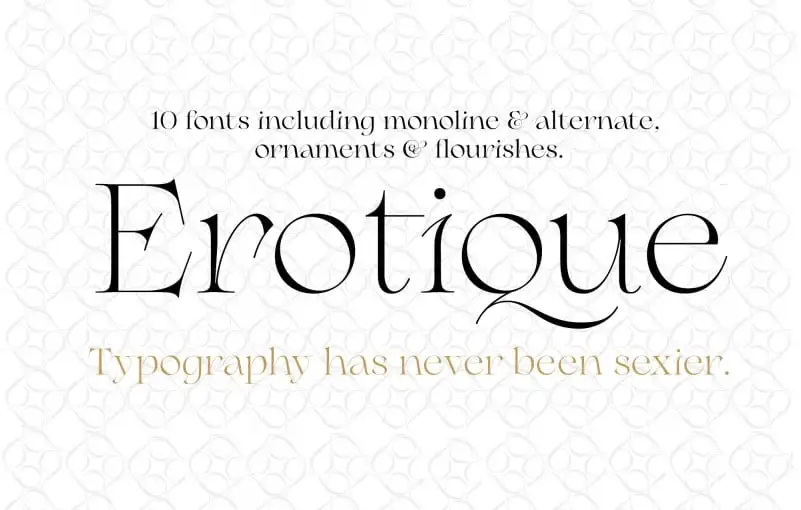
Erotique Serif Font Family – Fonte Grátis
Erotique Serif Font Family
Erotique Serif é uma tipografia serif que transmite um modernismo refinado e sedutor, uma combinação perfeita de elegância clássica e inesperada originalidade. Desenvolvida por Cosimo Lorenzo Pancini e Mariachiara Fantini com a ajuda da Solenn Bordeau, essa fonte evoluiu do design anterior da Zetafonts para Lovelace, que destacava os românticos contornos femininos. Erotique incorpora elementos modernistas transmodernos e neo-brutais na forma de linhas serifadas, com seus contornos esotéricos e borboletas chamuscadas, misturando imperfeições digitais com a caligrafia tradicional. Essa fonte possui uma aparência sedutoramente desafiadora, transmitindo os sentimentos de paixão oculta e amor recíproco ausente, ambas expressões carregadas de emoção. É perfeitamente adequada para qualquer projeto que exija uma tipografia romântica mas moderna, capaz de capturar tanto o calor dos contornos femininos quanto a delicadeza da linha pura e tradicional.